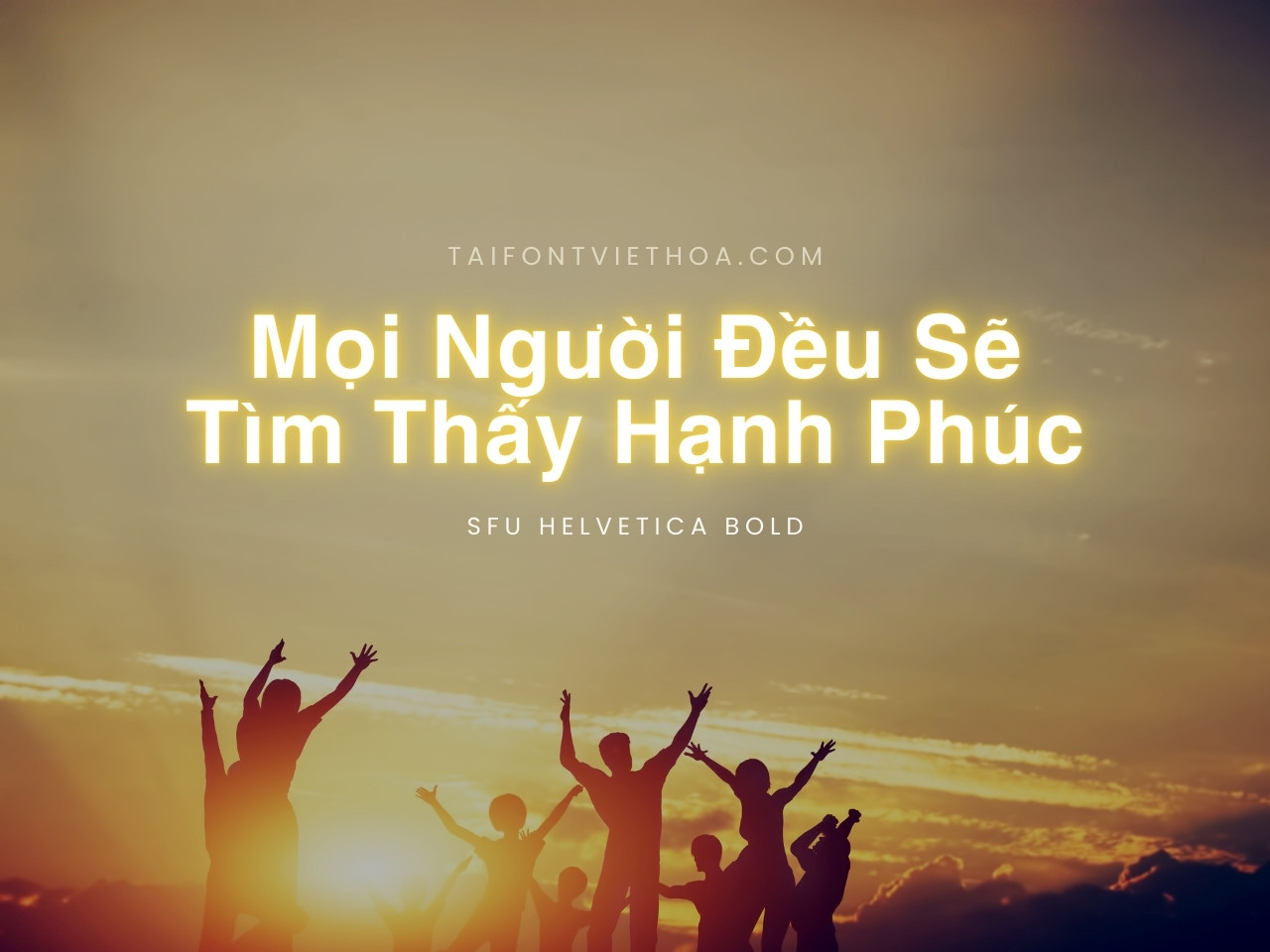
Font việt hóa SFU Helvetica
Giới thiệu về font SFU Helvetica – Biểu tượng tối giản của typography hiện đại
SFU Helvetica là phiên bản Việt hóa của font Helvetica huyền thoại – một trong những kiểu chữ sans-serif nổi tiếng và được sử dụng rộng rãi nhất trong lịch sử thiết kế đồ họa. Helvetica được thiết kế vào năm 1957 bởi Max Miedinger và Eduard Hoffmann tại Thụy Sĩ, với mục tiêu tạo ra một kiểu chữ trung lập, dễ đọc và mang tính toàn cầu. Trải qua hơn 60 năm, Helvetica đã trở thành lựa chọn hàng đầu trong nhận diện thương hiệu, thiết kế sản phẩm và giao diện số.
Phiên bản SFU Helvetica được Việt hóa công phu nhằm đảm bảo sự tương thích hoàn hảo với tiếng Việt, giữ nguyên tinh thần tối giản, cân đối của font gốc. Taifontviethoa.comđã sưu tầm và giới thiệu SFU Helvetica như một giải pháp tin cậy, chuẩn mực và linh hoạt cho mọi loại hình thiết kế – từ in ấn, bao bì đến UI/UX và quảng cáo.
Đặc điểm thiết kế chuẩn mực và tính ứng dụng vượt thời gian của SFU Helvetica
SFU Helvetica nổi bật với các đường nét thẳng, hình khối đơn giản, không chân và không có chi tiết trang trí. Cấu trúc chữ gọn gàng, tỉ lệ cân đối cùng khoảng cách giữa các ký tự được tính toán kỹ lưỡng giúp font đạt độ dễ đọc cao và tạo cảm giác chuyên nghiệp, tin cậy. Sự tối giản của Helvetica chính là yếu tố giúp nó thích nghi với hầu hết mọi loại hình thiết kế và ngành nghề.
Ứng dụng lý tưởng: hệ thống thương hiệu, bảng hiệu, hồ sơ doanh nghiệp, sách báo, website, ứng dụng di động, bao bì sản phẩm và cả các chiến dịch quảng cáo quy mô lớn. Ngành nghề phù hợp: công nghệ, tài chính, y tế, giáo dục, luật, bất động sản, thương mại điện tử và gần như mọi lĩnh vực cần sự rõ ràng, hiện đại và quốc tế hóa.